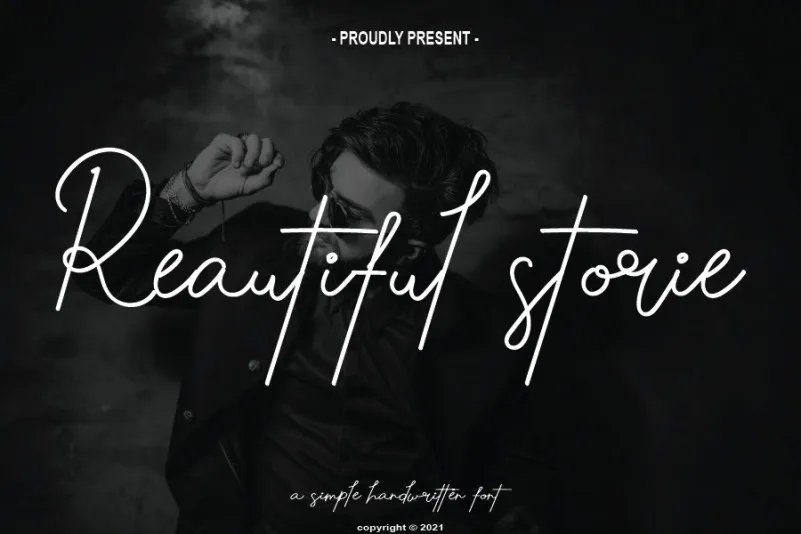
Este é um belamente equilibrado e refinado tipo de script que transmite sofisticação e elegância. A sua alternativa estilizada e ligaturas tornam esse tipo perfeito para qualquer projeto. Atenção: Não pode usar a fonte Reautiful Storie Handwritten Font para fins comerciais ou lucrativos sem autorização do criador/administrador, nem ao menos saber usar essa fonte sem autorização é punido com uma multa cinco vezes maior que o preço especificado. Esta fonte só pode ser usada em demos (licença de demonstração). Para usar a fonte para fins comerciais, por favor entre em contato através do email:  Este tipo de script está disponível apenas para uso educativo e não deve ser copiado sem autorização. A designer handwrittenwanda criou um tipo com estilo elegante, perfeito para gráficos, como nomes de lojas, logotipos ou mensagens personalizadas. Seja no seu site, no seu aplicativo, na sua embalagem, seja qual for o uso, garantindo que este tipo seja usado apenas dentro do escopo permitido protege-o contra futuras punições.